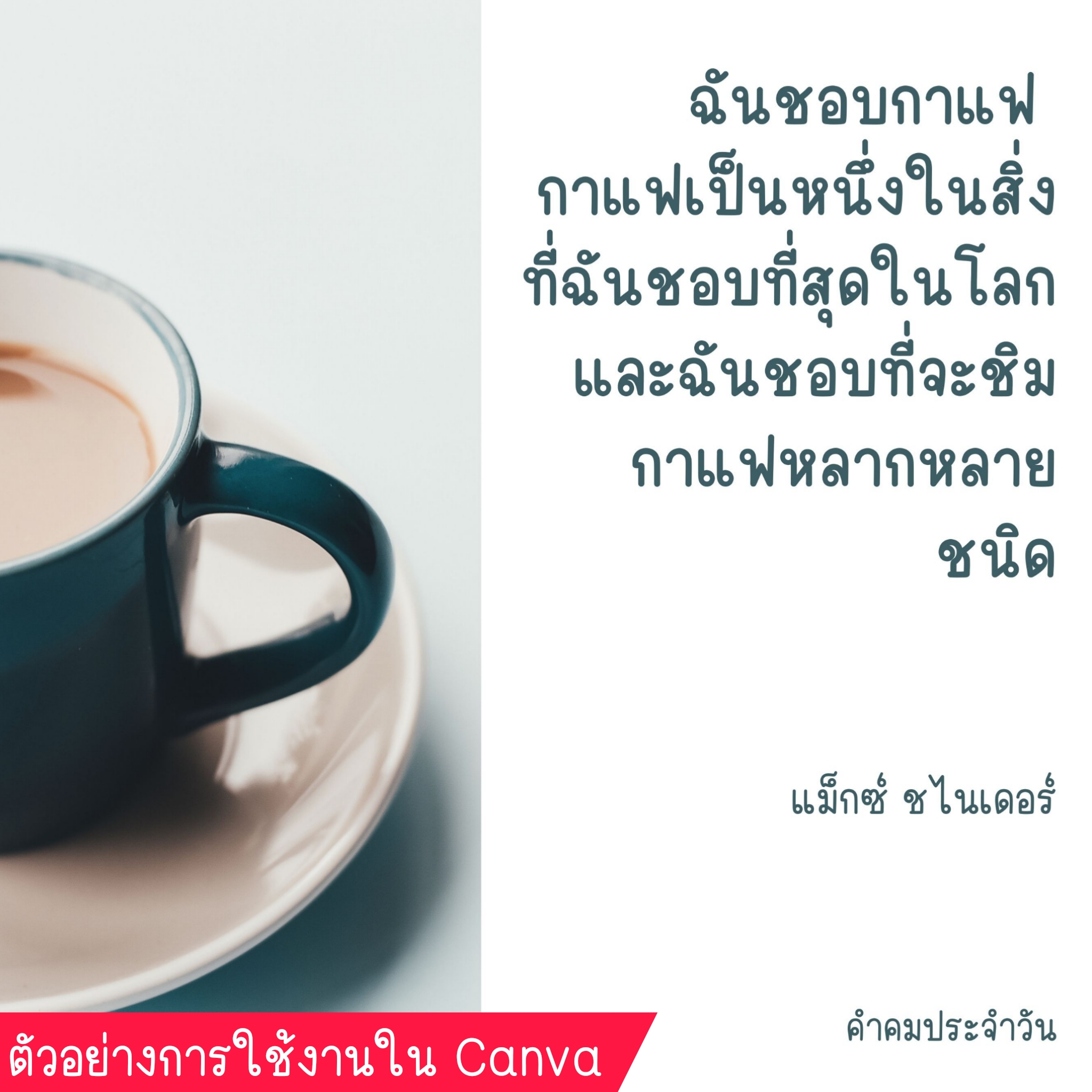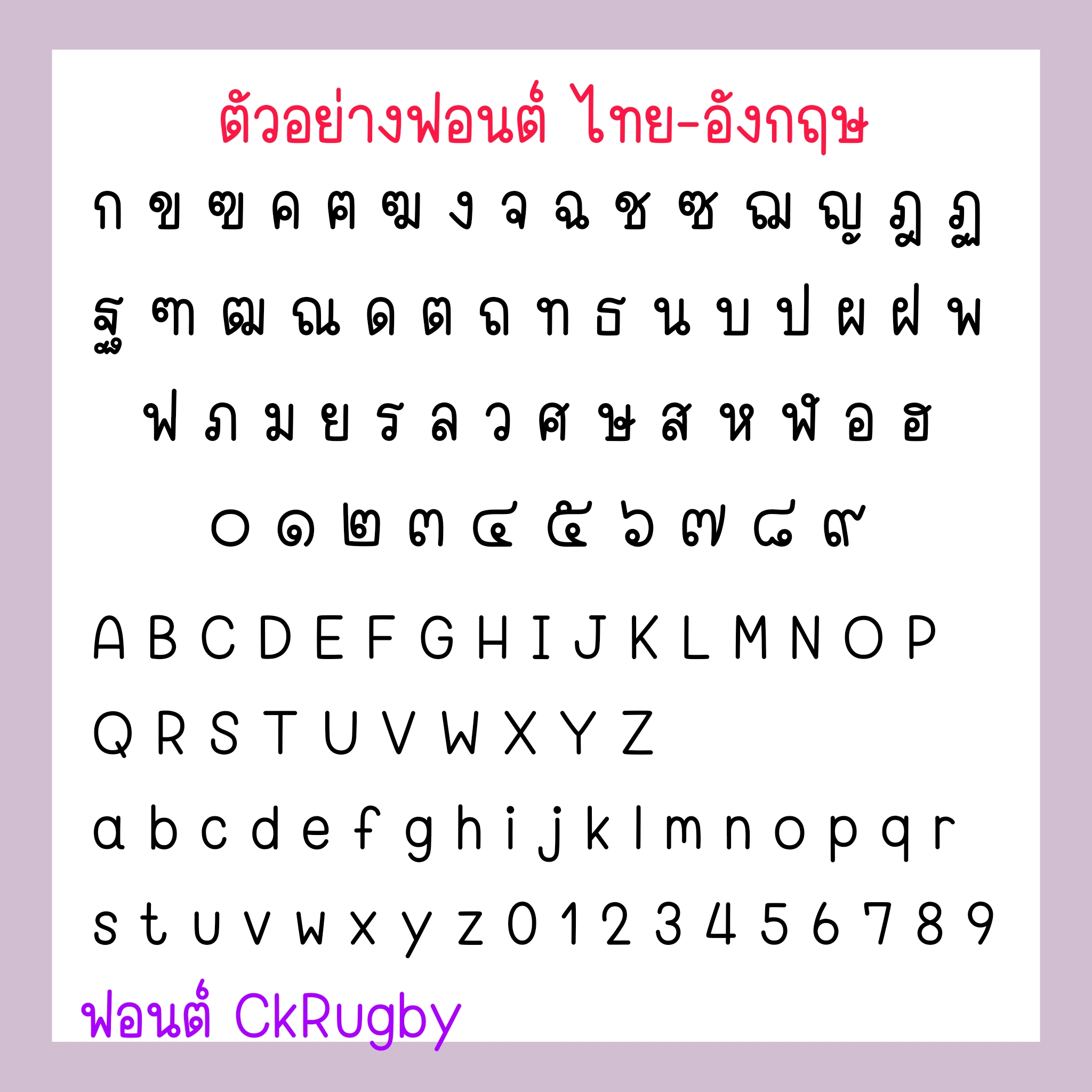
ชื่อฟอนต์ : ตะแล๊บแก๊ป๒๔๕๕
"จุด จุด ขีด จุด   ขีด ขีด ขีด   ขีด จุด   ขีด   ขีด ขีด จุด จุด ขีด"  ตะแล๊บแก๊ป..ฟอนต์ที่อ่านไม่ออก แต่ก็อ่านออกอยู่นะ รหัสมอร์สภาษาไทย (คล่องแคล่วแล้วให้กด bold)
Collage House
แจมโรลส์ (PG Jamrolls)
ฟอนต์ลายมือสไตล์น่ารักปุ๊กปิ๊ก อ่านง่าย รองรับ Microsoft, Photoshop, Illustrator, CapCut, ibisPaint, Procreate, Good Note และแอปฯ ต่างๆ ที่มีให้ติดตั้งฟอนต์
พอ จะ นะ
SP_KanEng กันเอ็ง
FontHouse
ฟอนต์กู๊ดแลนด์ ( FH GoodLand )
ลายมือสไตล์น่ารักปุ๊กปิ๊กใช้งานได้ทุกโอกาส
เวอร์ชั่นเต็ม มี 3 น้ำหนัก
บ้านน.fonts
ฟอนต์เจ้ามะเขือเทศ 🍅
ได้ฟอนต์เต็มเวอร์ชั่น 3  ขนาด
( ☑️เส้นหนา ☑️เส้นบาง ☑️เส้นปกติ)
แจกให้ใช้งานฟรี ! สำหรับคนที่ชอบฟอนต์ลายมือ น่ารักๆ เรียบร้อย ตัวเล็กๆ
เพิ่มความน่ารัก x10! ให้งานเขียน ทำรายงาน แต่งสตอรี่ หรือใส่รีวิวสินค้าคือจึ้งงง
✍🏻แนะนำว่า นำไปใช้งานกับการจดเนื้อหา สรุปงาน จดโน๊ต จดบันทึก
หรือจะนำไปทำคลิป แต่งรูป ก็เริ่ดสุดๆ แนะนำเลย
- ฟอนต์ CkRugby ฟอนต์ลายมือแนวเรียบร้อย เน้นความเป็นระเบียบ อ่านง่ายสบายตาค่ะ
KirakiraFontverse